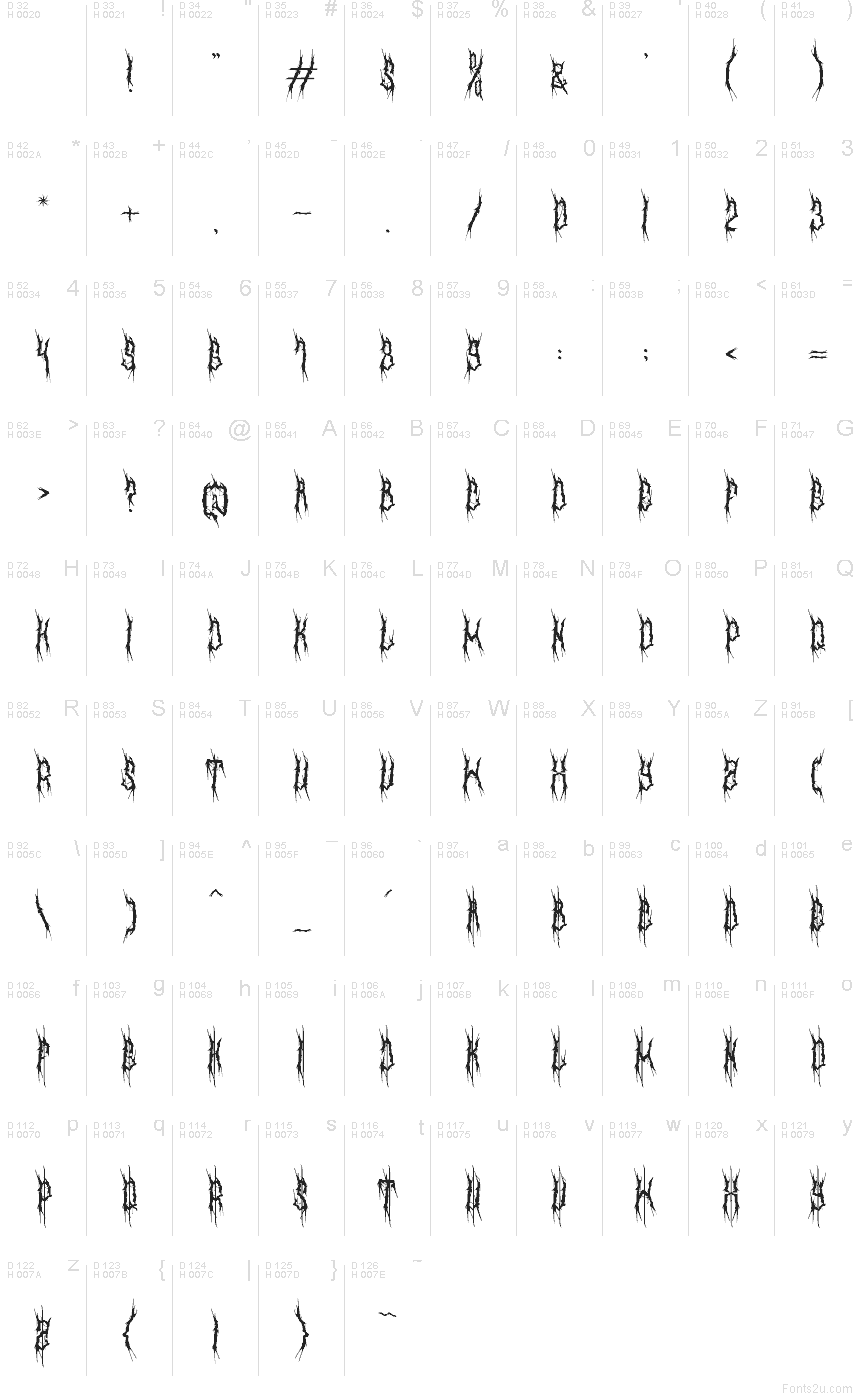
Oblivor od Putracetol Studio je bezplatné hororové písmo typu display s ostrým black-metalovým nádechem. Písmena vypadají jako vyřezaná z trní a třísek; vysoké, jehlovité tahy, hákovité spoje a roztřepené hrany dodávají celému fontu napjatý, nepřátelský rytmus.
Hodí se pro loga kapel, titulky plakátů, úvodní obrazovky her, obálky hororů a okultní branding, kde je potřeba syrový, rituální dojem místo čistého studiového vzhledu. Používejte ho v krátkých blocích – titulky, merch, začátky kapitol nebo monogramy –, protože ty drátěné hroty a drápovité siluety udělají hlavní vizuální práci okamžitě.